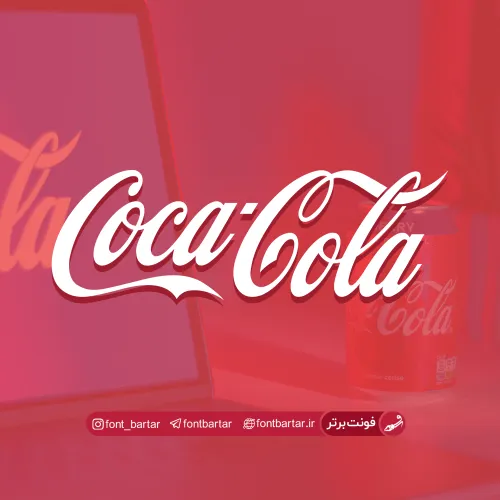
فونت انگلیسی CocaCola
فونت گرافیکی با ساختار پیچیده که در دسته فونت های لاتین قرار دارد و طرفداران زیادی دارد ، این فونت اورجینال کمپانی و برند کوکا کولا است ، که البته بد نیست بدانید نام این فونت Lokicola است که همراه آن سنبل CocaCola نیز ضمیمه فایل شده است ، که تمامی لوگوتایپ های کوکا کولا را دارا است ، فونت انگلیسی CocaCola به صورت کاملا رایگان در فونت برتر در دسترس است.